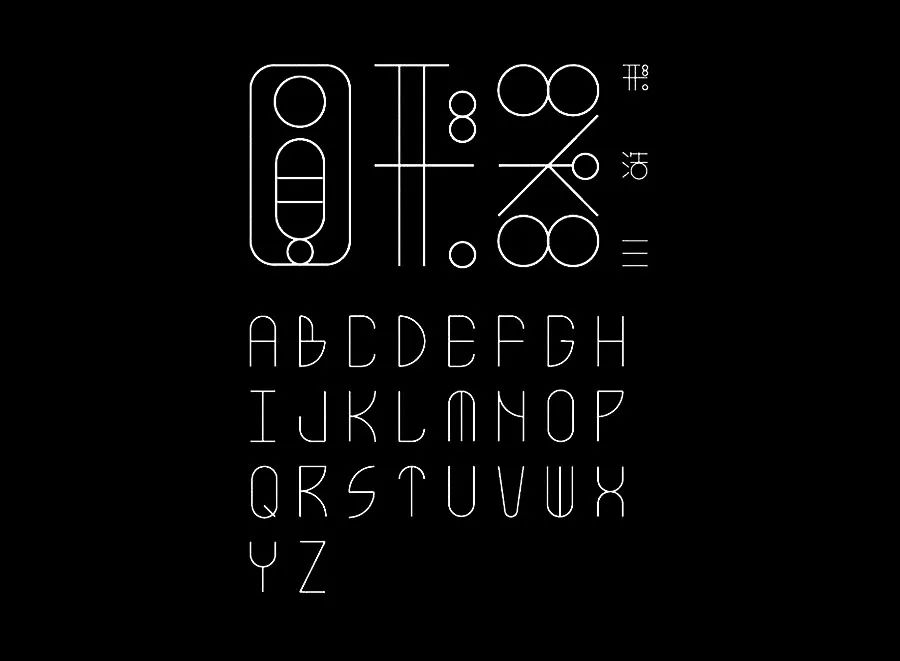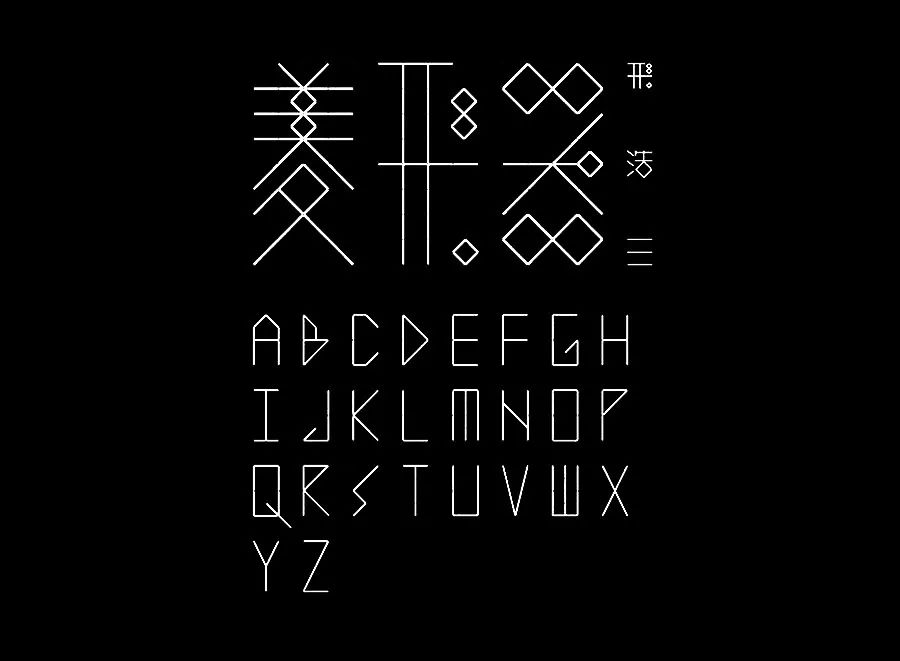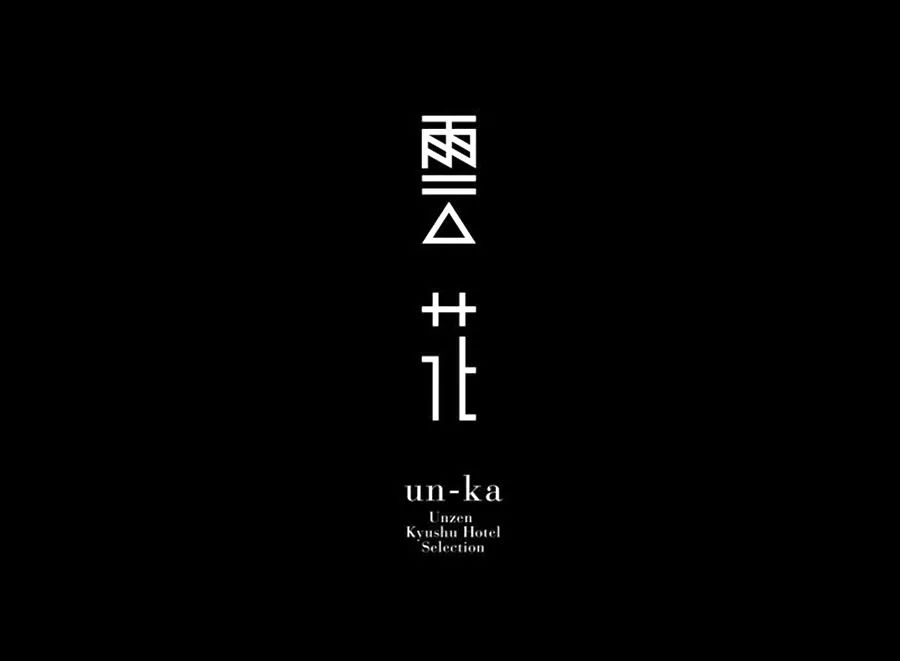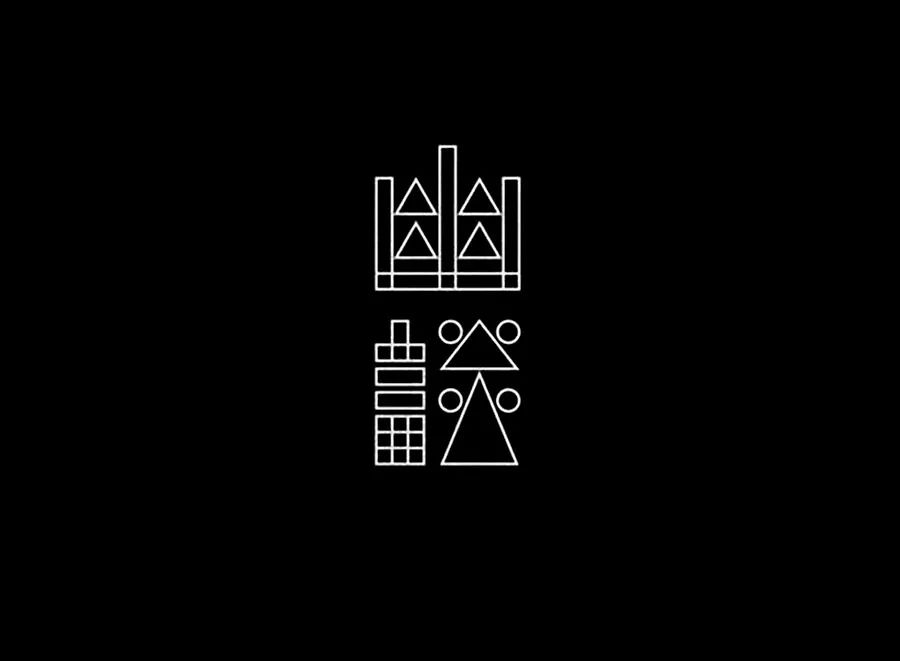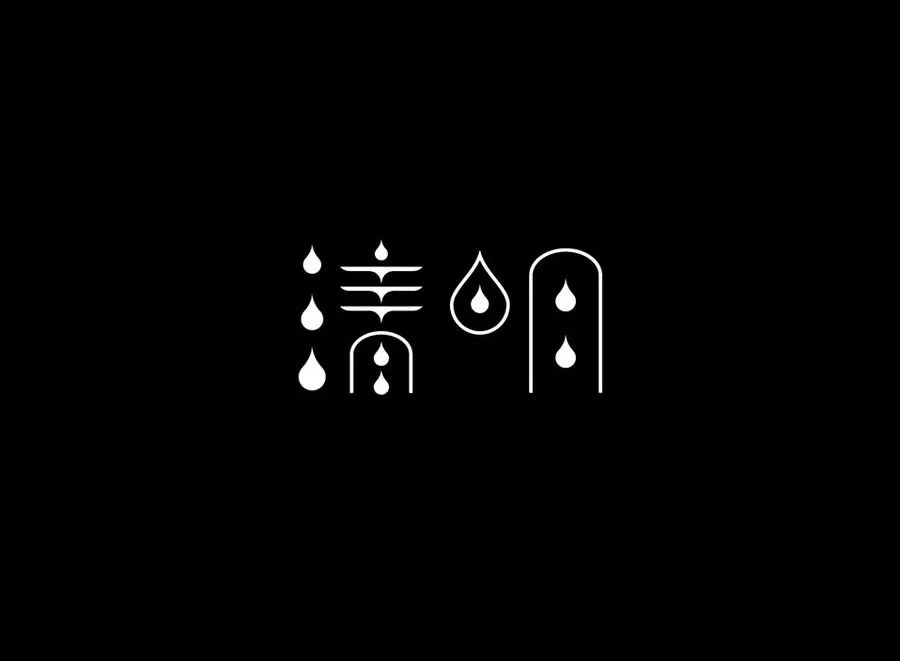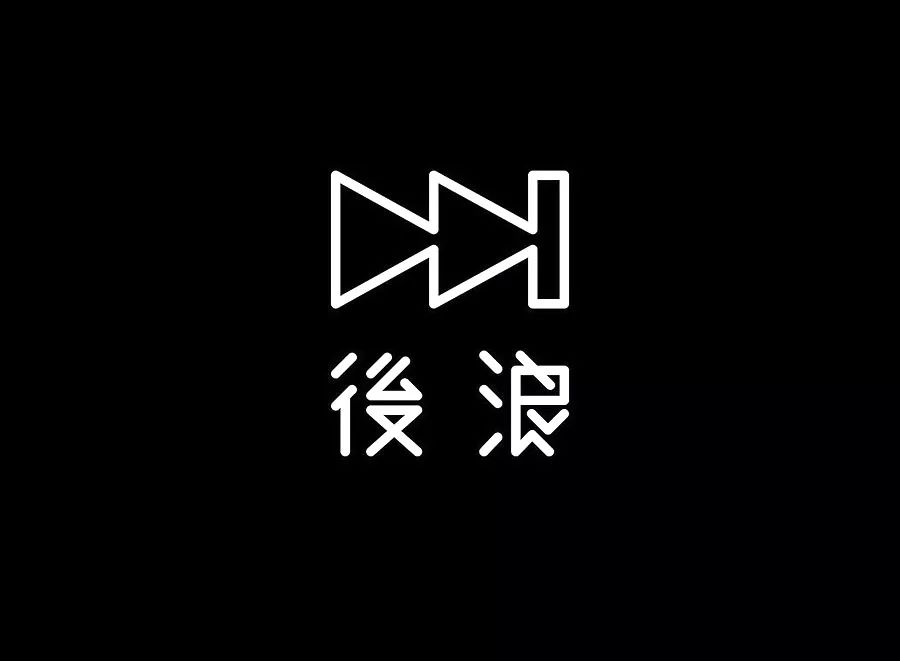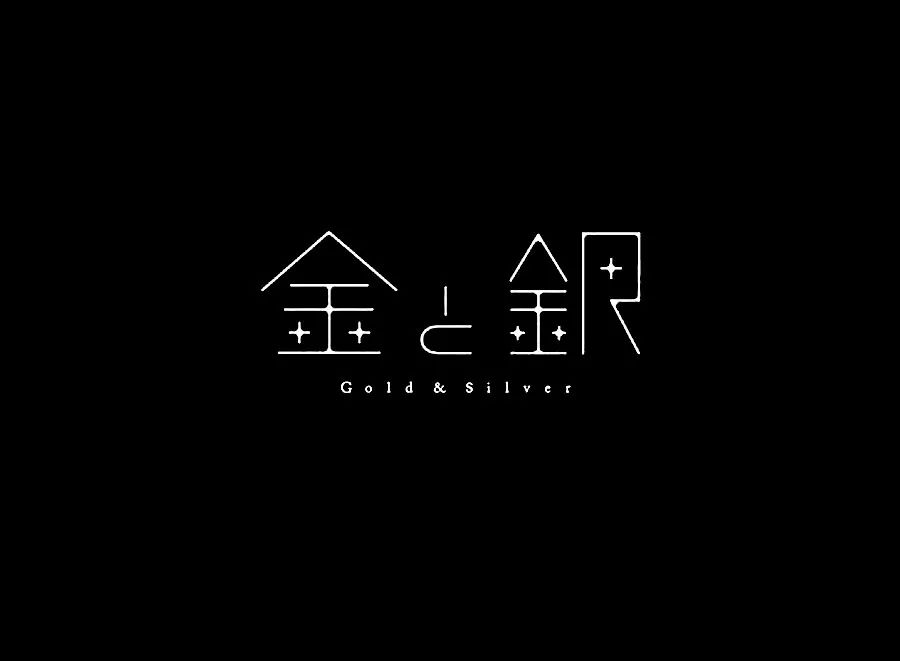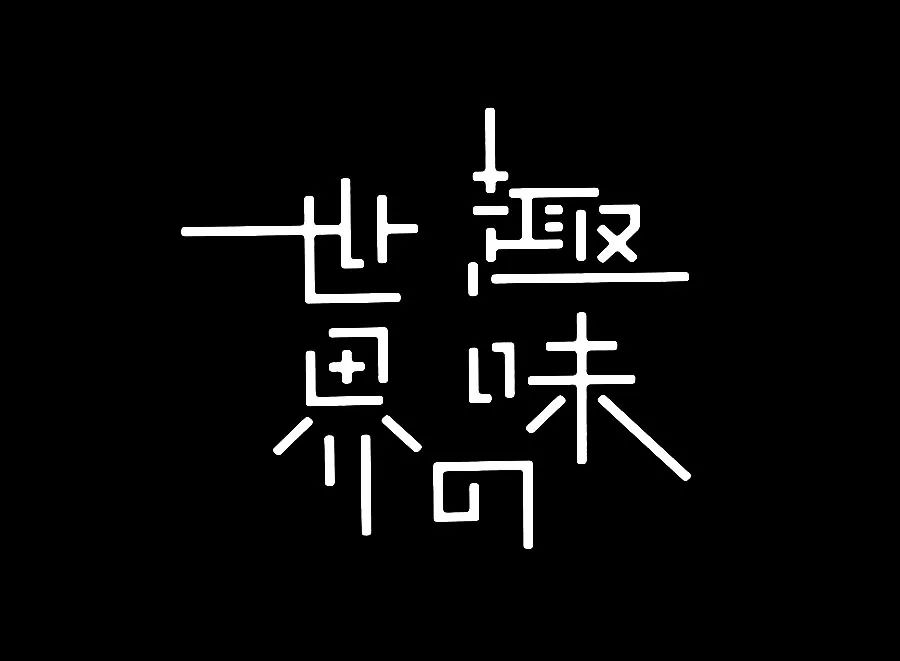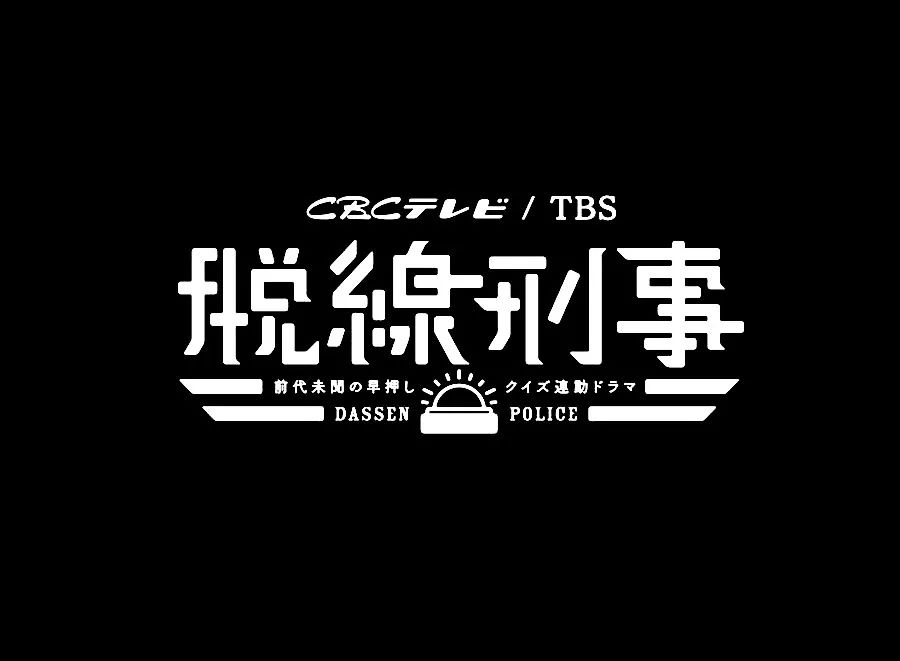
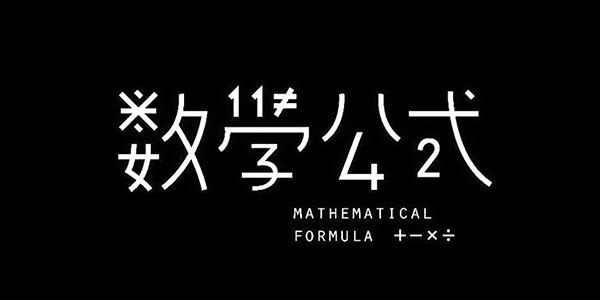
这次字体设计没有特殊要求,做的有设计感一点就可以了...
大家好,又跟大家见面了,今天更新的文章是让字体设计更加具有设计感的方法,希望大家喜欢!本篇文章举了三种比较宏观上的方法,但是方法不仅有这三种。再举例之后还会有案例演示帮助大家消化与理解。
下面进入正文吧,宏观上的方法有以下三个
虽然我称此方法为几何置入,但并不是特指三角圆形等几何形状,其他的形状或符号也包含在内。
通常几何置入法是将字体中的某个或某组笔画以形状或符号的方式替换,使之看起来更具有设计感。
上图右侧的“夢”字进行了几何化的替换笔画处理更具有设计感,当然识别性也变差了,但右侧的“夢”是用作海报的主形象的,更多的是传达一种概念,所以识别性差也没有影响。
那么我们看一下几何置入法的优秀作品
结构变化即改变字体的结构,简单来说就是对字体进行笔画的增加和删减,使其更具有设计感。
当然,结构的变化是非常难的,掌握不好就会将字体做的不伦不类。除了笔画的增加与删减,结构变化还包括将笔画的形态改变,比如点笔变竖笔,斜笔变横笔等等。
同样的字体经过结构变化后,设计感会提升不少。
下面看一下结构变化法的优秀作品
其实我所说的这三个方法是可以组合使用的,比如上图的作品既用了几何置入又用了结构变化,如果愿意还可以加入维度的变化。
第三种方法就是添加维度了,将字体从二维平面转化到三维层面,多加一个维度使其更具有空间感跟立体感,二维转成三维后一样能提高设计感。
一个普通的黑体字形只加入一些空间的线条就能将立体感拉开,从而更具有设计感。
下面看一下添加维度法的优秀作品
因为几何置入与结构变化经常一起出现,所以就将他们归为一个案例进行演示。
第一个案例做“雲中游”三个字,首先将三个字用字库字的形式打出来。
雲中游给人的感觉轻盈的,那么扁宽的字型甚至是方块字表达的气质都差那么一点,相反瘦高型的字型能够更好的表现轻盈的感觉,所以我们将字体压瘦,并将间距拉松一点使之更有轻盈的感觉。
做到此之后要对字进行观察,看一看那些字型的部件能用几何图形的方式替换。下图是经过观察之后找出可以替换的部分。
做到此步之后就可以正式做字了,将字造型的骨骼搭建好,并将可用几何图形的部件替换,基本字形就差不多了。
基本字形完成后我们可以用第二种结构变化法进行加工,使之更具有艺术性。下图是我用结构变化里的笔画连接法处理过的。
还可以再笔画交叉连接的地方倒角处理,使之更具有艺术感,如下。
那么做到此步这组字就完成了,下面是反白与墨稿
最后看一下这组案例的GIF过程图。
添加维度就很好理解了,就是使平面的东西立体化。所以这个案例我就简单说一下,以“立”字为例。
首先我们要将字体的骨骼搭建出来,骨骼及结构,做完结构后可以适当更改描边粗细到合适大小,如下
调整笔画粗细始终之后就要加入立体感的特征了,我们可以在笔画末端做处理,使笔画与笔画间有种前后的关系,如下
也可以直接给字体加入一个面,使之增加一个维度,如下
简单的说增加维度不管用任何方法都可以,不只有本例中的两种形式,其他的像是加字效或是用三维软件渲染都是不错的选择。